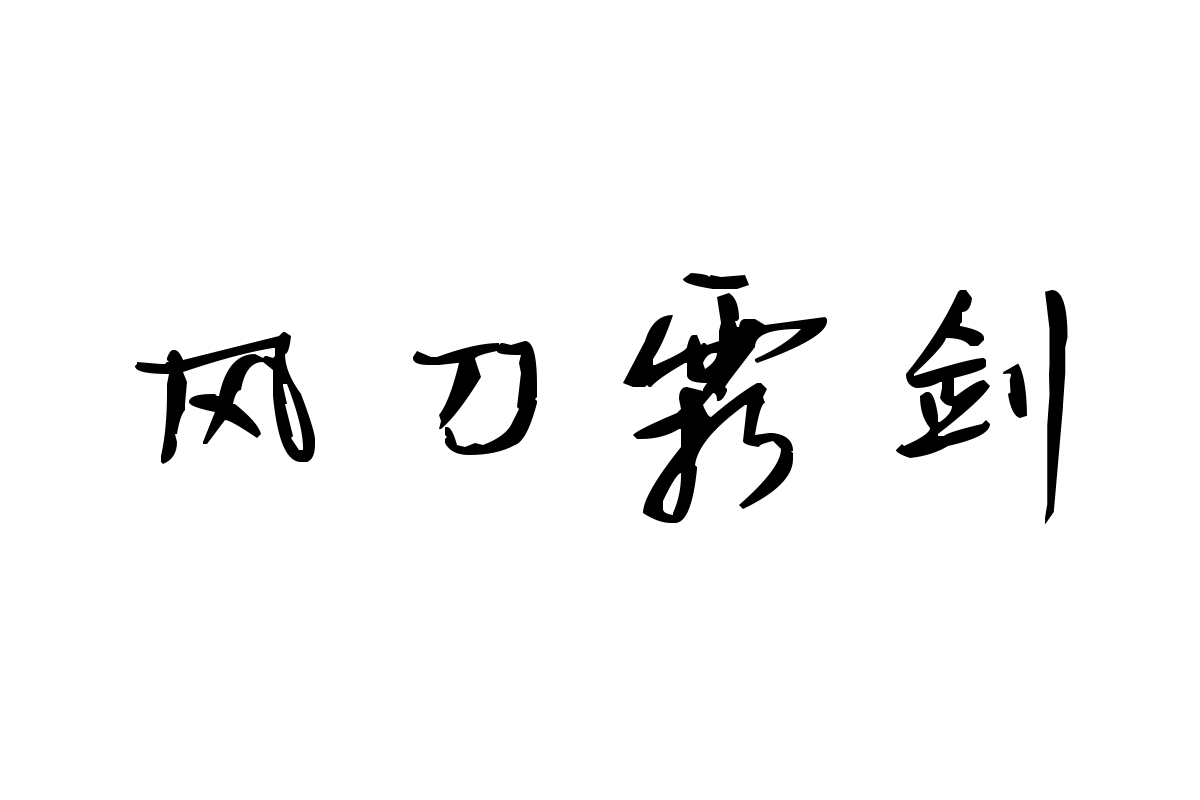
米开偷偷爱着你字体是一种具有独特魅力的中文字体,它以其独特的设计和风格吸引了众多用户的喜爱。这种字体的特点在于其线条流畅、结构紧凑,给人一种简约而不失时尚的感觉。
在设计上,米开偷偷爱着你字体采用了简洁明了的笔画,使得整个字体看起来更加清晰易读。同时,它的字形结构紧凑,线条流畅,给人一种优雅而高贵的感觉。无论是用于标题还是正文,都能展现出一种独特的美感。
此外,米开偷偷爱着你字体还具有一定的艺术感,它能够很好地与各种设计风格进行搭配,无论是现代简约还是复古文艺,都能展现出不同的韵味。这使得它在设计领域得到了广泛的应用和认可。
总之,米开偷偷爱着你字体以其独特的设计风格和易读性,成为了众多设计师和用户的首选字体之一。无论是用于广告、海报、网页还是其他设计项目,它都能展现出一种独特的美感和艺术气息。